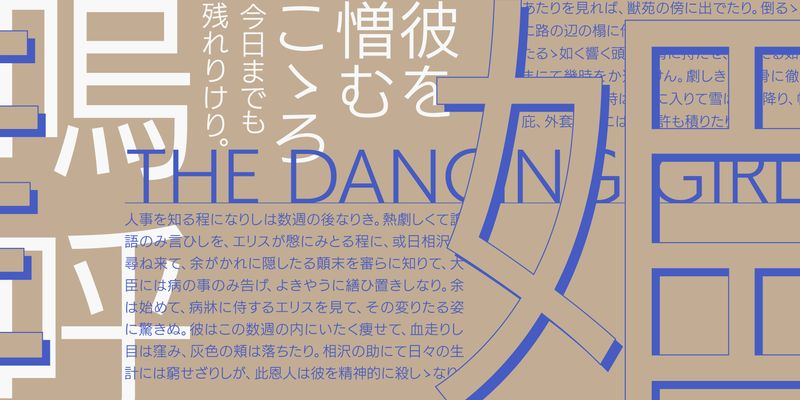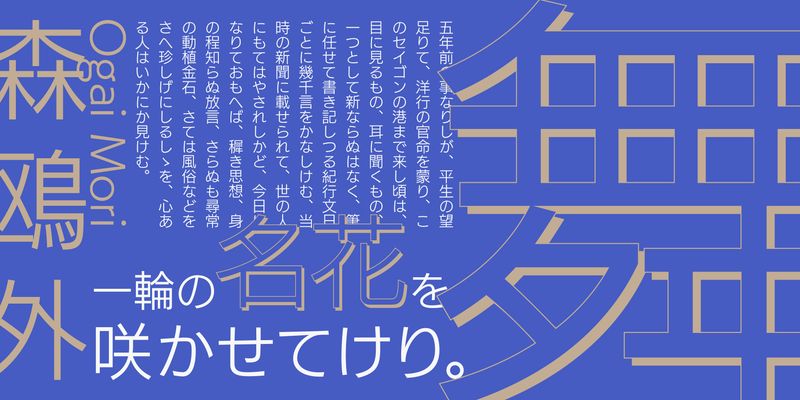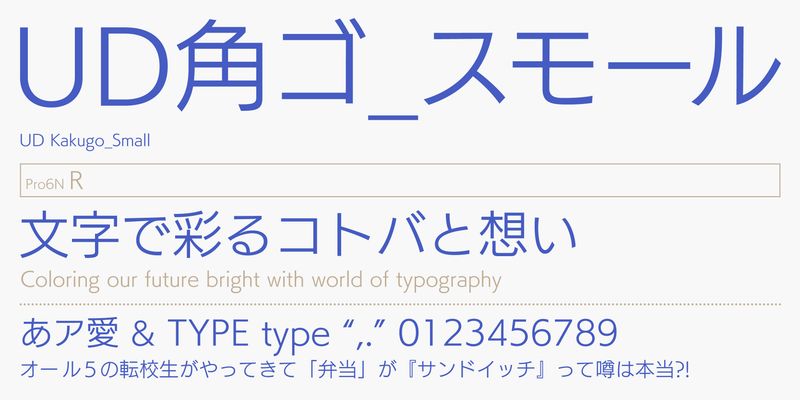
Questo carattere è basato su UDKakugo_Large, ma è stato riprogettato per essere adatto a testi lunghi. Per migliorare la leggibilità, la dimensione dei glifi latini e numerici è stata ridotta del 6% e la dimensione dei glifi kana è stata regolata, quindi questi glifi sono ben bilanciati tra loro e il carattere tipografico è più leggibile. Questa versione più piccola della famiglia di caratteri UDKakugo è efficace per testi lunghi.